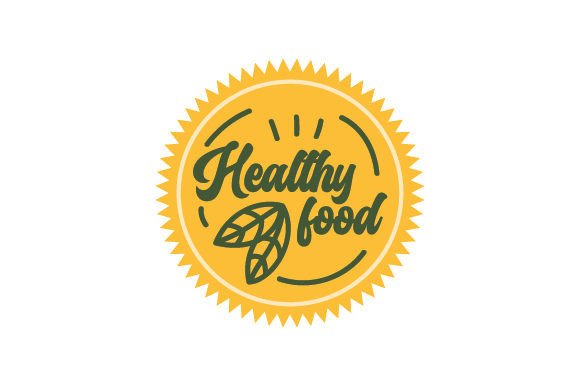
Retro Fruit Label - Healthy Food
Việc tìm kiếm các thành phần thiết kế phù hợp có thể là một thách thức, nhưng Retro Fruit Label - Healthy Food cung cấp một bộ sưu tập đặc biệt giúp nâng tầm công việc của bạn ngay lập tức.